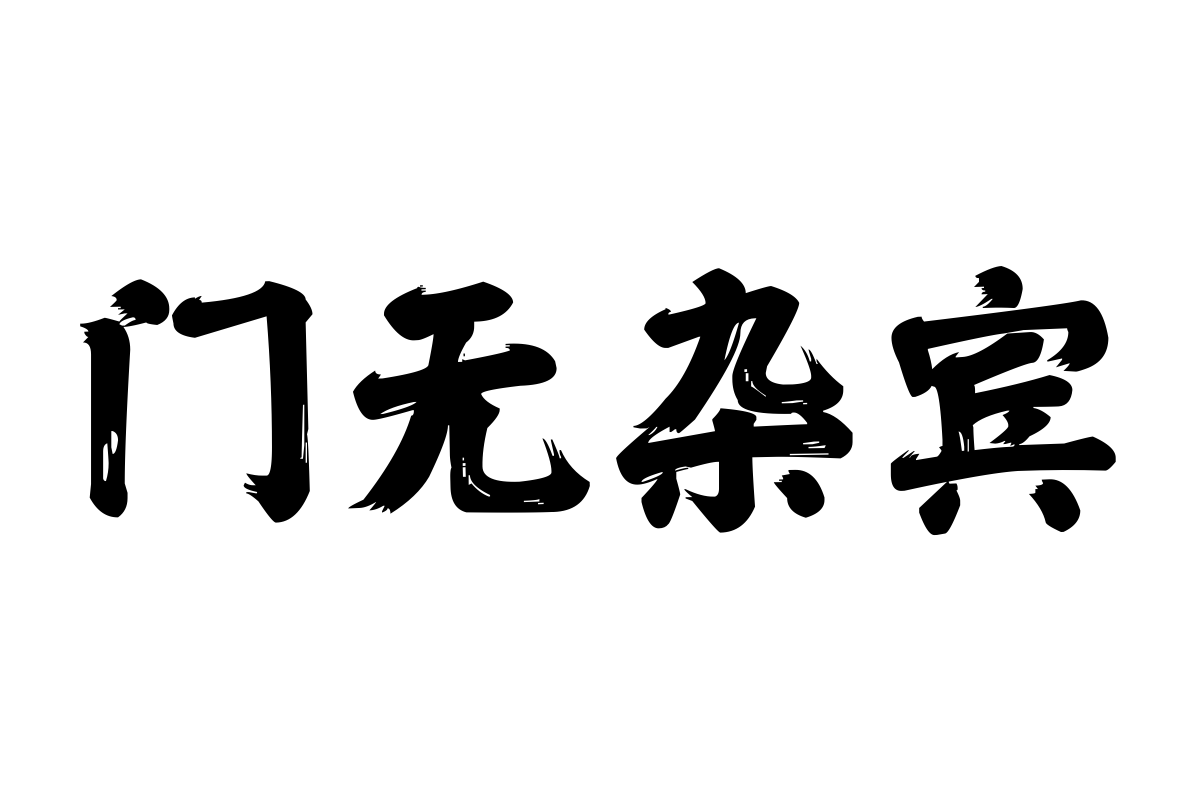
汉仪新蒂佛塔书是一款具有独特风格的中文字体,由汉仪字库出品。这款字体的设计灵感来源于佛教建筑中的佛塔,因此得名“新蒂佛塔”。其特点是字形圆润饱满,线条流畅自然,给人一种庄重、宁静的感觉。
新蒂佛塔书采用了多种不同的字形组合,包括楷体、行书、草书等,以适应不同的书写需求。同时,这款字体还融入了一些现代设计元素,使其更加符合现代人的审美习惯。
总的来说,汉仪新蒂佛塔书是一款适合用于书法、海报、广告等多种场合的中文字体。它以其独特的风格和广泛的应用范围,受到了许多设计师和用户的欢迎。